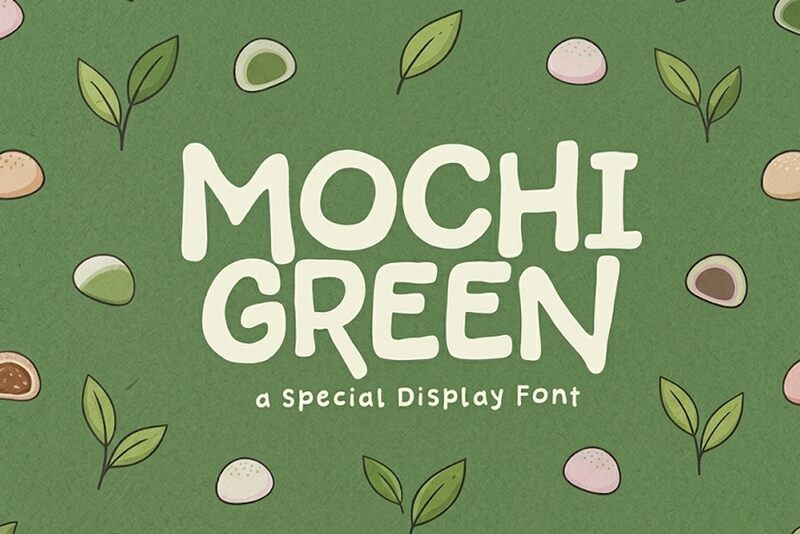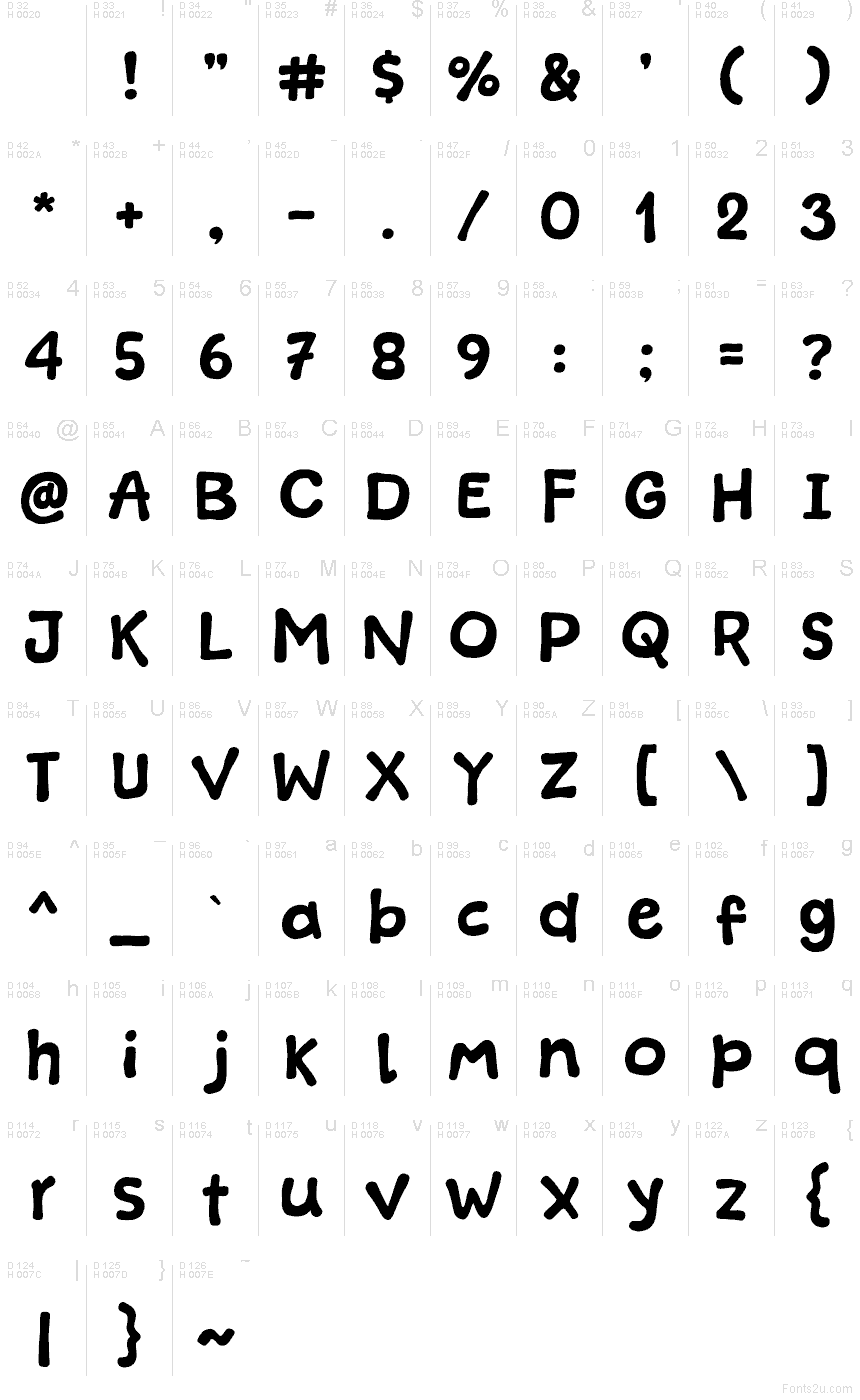
Mochi Green, di Khurasan & Jalembe, è un font display gratuito in stile cartoon, caratterizzato da lettere morbide e gonfie che richiamano un aspetto artigianale e giocoso. Le forme arrotondate, il ritmo irregolare e il carattere gommoso conferiscono al font un tono amichevole e spensierato, senza risultare stucchevole.
È perfetto per packaging di snack, inviti a feste, copertine di libri per bambini, insegne di locali e post social allegri dove serve un font gratuito con una voce disinvolta. Usalo per titoli brevi, loghi o grandi intestazioni: le curve corpose e l'andamento casuale rendono al meglio quando le lettere hanno spazio per respirare.